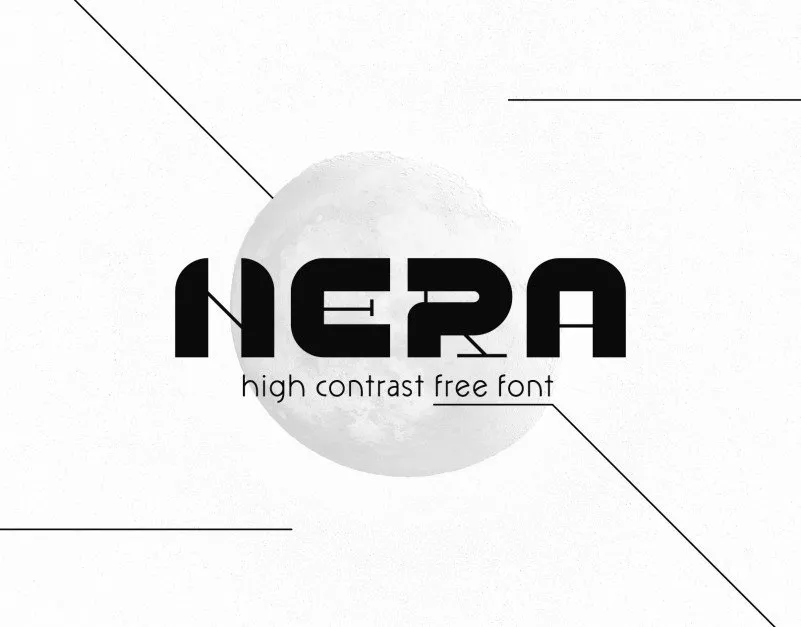
NERA Display Font – Fonte Grátis
NERA Display Font
A NERA Display Font é uma fonte geometricamente geométrica com contraste alto que se destaca tanto na digital quanto nas aplicações impressas. Esta fonte está disponível em diferentes graus: a versão “Nera heavy” é gratuita, enquanto a família completa — que inclui bold, regular e light — pode ser adquirida sob licença. A NERA foi projetada usando uma grade geométrica quadrada para criar um grande contraste entre espaços brancos e pretos dentro dos caracteres. Esta fonte perfeita para aplicativos modernos é a escolha ideal para qualquer marca que deseja dar um toque de destaque em seus materiais digitais. Com seu contraste poderoso, você pode transformar mensagens simples em texturas impactantes, tornando-a uma ferramenta indispensável para designers gráficos. Além disso, a NERA é adequada para criações visuais modernas, como menus de aplicativos ou publicações, dando um toque elegante e atemporal às suas produções. Com o designer italiano DanieleFranchi trazendo sua habilidade única ao processo criativo, os designers podem encontrar facilmente a combinação perfeita de design e funcionalidade. Seja em uma plataforma digital ou impressa, NERA Display Font é sempre um ótimo investimento para qualquer projeto visual exigente.